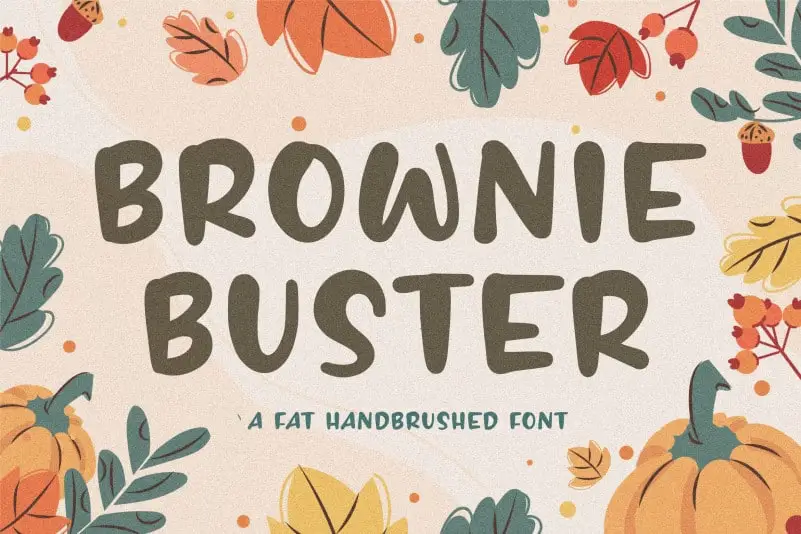
BROWNIE BUSTER Fat Handbrushed Font – Fonte Grátis
BROWNIE BUSTER Fat Handbrushed Font
A fonte “Brownie BUSTER Fat Handbrushed Font” é uma escolha perfeita para designers que procuram um estilo artesanal e elegante. Inspirada nas técnicas de desenho a mão, essa fonte oferece uma textura única e vibrante, ideal para aplicação em embalagens de produtos, marcações, publicações de revista, mídias sociais, casamentos ou simplesmente como forma de destacar texto sobre um fundo. Suas linhas levemente suaves e traços expressivos criam uma aparência cuidadosamente realizada, adequando-se perfeitamente para qualquer projeto visual que valorize a personalidade da marca. Com certeza, ela é o elemento adicional que seu design precisava para se destacar.